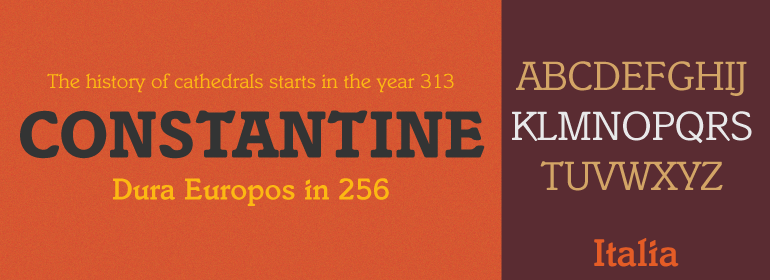
Italia™
Italia字体是Colin Brignall的作品,这是一款令人耳目一新的衬线字体。乍一看,Italia似乎可以与其他任何方形衬线字体相媲美,但是它具有独特的样式。Italia字体既可以用作显示字体,也可以用作文本字体,而且能够为任何文本提供一种独特的外观。
Italia font is the work of Colin Brignall, a refreshingly different serif typeface. At first glance, Italia might seem comparable to any other square serif typeface, but it has a distinctive pattern all its own. Italia font can be used as either a display or text font and will give any text a unique look.